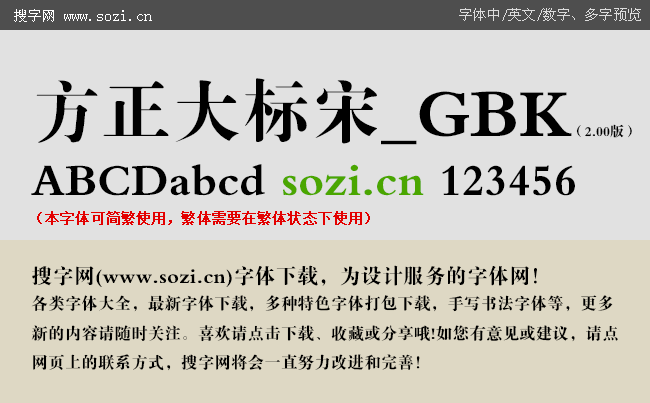
方正大標(biāo)宋_GBK
搜字網(wǎng)提供一款方正大標(biāo)宋_GBK中文字體下載,方正大標(biāo)宋是一款非常端正的中文字體,適合在正式的場(chǎng)合來(lái)進(jìn)行使用,GBK編碼收字更全,適合應(yīng)用于廣告設(shè)計(jì)、名片設(shè)計(jì)、包裝印刷、產(chǎn)品設(shè)計(jì)等應(yīng)用。